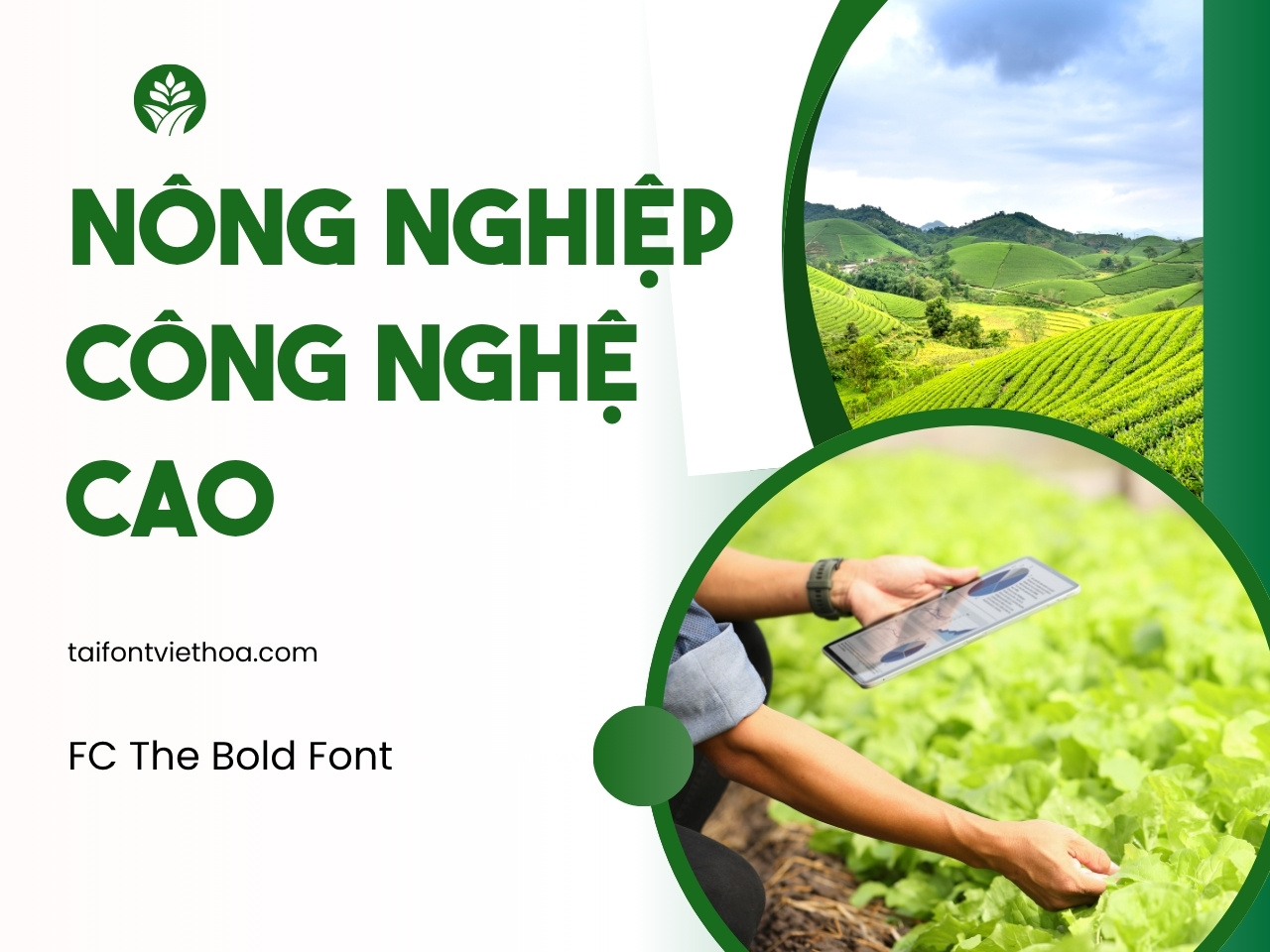
Font việt hóa FC The Bold Font
Tác giả Font: Sven Pels
Giới thiệu về font The Bold và phiên bản Việt hóa
FC The Bold Font là một phiên bản Việt hóa độc lập từ font gốc “The Bold Font” – một phông chữ sans-serif mạnh mẽ do nhà thiết kế Sven Pels (Hà Lan) sáng tạo. Với hình khối dày dặn, đường nét rõ ràng và độ tương phản cao, font này thường được sử dụng trong các thiết kế tiêu đề lớn, poster quảng cáo, hay truyền thông thị giác cần sự nổi bật. Font gốc hỗ trợ hơn 70 ngôn ngữ thuộc bảng Latin và được phát hành miễn phí, nhờ đó nhanh chóng trở thành lựa chọn phổ biến trên toàn cầu.
Khác với bản “1FTV The Bold Font”, phiên bản FC The Bold Font do cộng đồng Font Chuẩn Việt hóa được thực hiện một cách độc lập và kỹ lưỡng. Bộ ký tự tiếng Việt được bổ sung đầy đủ với các dấu thanh được thiết kế hài hòa, giữ vững cấu trúc hình học nguyên bản mà vẫn tương thích hoàn toàn với ngữ cảnh sử dụng tiếng Việt. Font đã được taifontviethoa.com chọn lọc, kiểm tra và chia sẻ miễn phí, đặc biệt phù hợp cho các nhà thiết kế đang tìm kiếm một phông chữ sans-serif đậm nét, hiệu quả trong branding, tiêu đề và ấn phẩm quảng cáo mạnh mẽ.
Phong cách thiết kế và ứng dụng đa dạng của The Bold Font
The Bold Font thể hiện đúng tinh thần “bold” – đậm, chắc, rõ ràng. Với cấu trúc sans-serif hiện đại, độ dày đồng đều và độ tương phản thấp, font này giúp truyền đạt thông điệp một cách trực tiếp, dễ đọc và dễ nhìn trên mọi nền tảng. Font có khả năng hiển thị tốt ở cả kích thước lớn và nhỏ, phù hợp cho tiêu đề, bảng hiệu, banner và logo thương hiệu.
Ứng dụng của font trải rộng trong nhiều lĩnh vực như bất động sản, quảng cáo, thiết kế ẩm thực, bảng hiệu công ty, công nghệ, giáo dục và các dự án branding hiện đại. FC The Bold Font cũng là lựa chọn lý tưởng cho các chiến dịch quảng bá nhân dịp Tết, lễ hội, sinh nhật hoặc các dịp đặc biệt nhấn mạnh vào thông điệp thị giác mạnh mẽ.